Акцидентные кириллические шрифты — Дизайн на vc.ru
Сейчас набирает обороты тренд, когда в основе айдентики лежит типографика. В подтверждение этому есть 2 классных кейса на Behance (не реклама 😉):
Чтобы сделать крутую айдентику на основе шрифта — он как минимум должен быть необычным и читабельным в заголовках. Поэтому я решил сделать подборку крутых декоративных шрифтов, которые в теории могли бы лечь в основу айдентики какого-то крутого проекта.
1. CSTM Xprmntl 03
Этот вариативный шрифт по сути содержит в себе 3 разных шрифта. Так как многие компании активнее развиваются в digital, вариативные шрифты стают все более актуальными, потому что они могут добавить динамики к айдентике проекта с помощью моушена
Flicker
Еще один вариативный шрифт с эффектом искривления, который легко можно примерить и в дизайн-системе. Но это не главное, сам по себе шрифт довольно характерный и необычный, при этом будет хорошо читаться заголовках
3. Miratrix
В основе шрифта лежат две фигуры — круг и квадрат. Не смотря на строгую геометрию шрифт не кажется серьезным, а наоборот создает восприятие протеста. Сама его форма говорит за себя «Я не такой, как все». Этот шрифт точно привлечет внимание к бренду, а в комбинации с уникальными визуальными элементами в дизайне можно создать очень смелый и впечатлительный стиль
4. Songer Grotesque
У этого семейства есть еще 2 шрифта — SemiExpanded и Condensed.
Но в подборку я решил включить именно Songer Grotesque, так как он является самым интересным. По сути это микс SemiExpanded и Condensed, где буквы округлой формы взяты из SemiExpanded, а все остальные из Condensed. Такая комбинация добавляет контраста шрифту и делает его уникальным и выделяет на фоне других. Этот шрифт я использую у себя на сайте, кто хочет посмотреть его в работе, welcome → https://3-14.me
5. Polonium
Урбанистический шрифт. С ним нужно быть осторожным, так как не все буквы воспринимаются как надо. У шрифта так же есть строчные глифы и bold-начертание.
6. Moniqa
Элегантный шрифт, я бы использовал его в проекте, где преимущественно женская ЦА. У шрифта уйма начертаний, много интересных лигатур, комбинируя их можно сделать как мега-необычную, так и довольно сдержанную типографическую композицию
Durance Type
Шрифт моего коллеги по цеху Вани Цанко. Вдохновлен цветочными орнаментами. Идеально подходит для больших макетов. В шрифте есть 2 стилистических сета: с более строгой и более мягкой геометрией
8. Rebel Type Dog
Интересный шрифт, который напоминает ретро, но в современной интерпретации. У шрифта строгая модульная анатомия, за счет чего все глифы выглядят целостно и придерживаются единого стилистического решения
Шрифт и контент | Блог Смартпринт.рф
Часто текст расценивают, как контент (смыслы) и забывают о его роли, как о графическом элементе (выбор шрифта).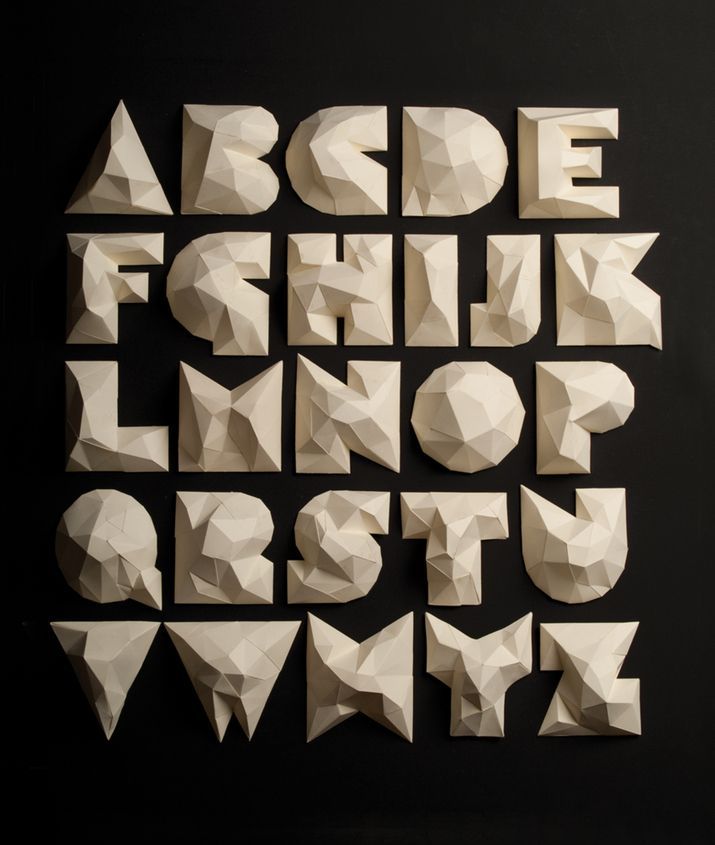
Сила смыслов должна быть подкреплена силой визуализации
Вопросы, которые возникают при работе с шрифтами:
- Как выбрать шрифт?
- Какие параметры необходимо учитывать, чтобы подобрать шрифт для макета?
- Где найти бесплатные шрифты?
Шрифт — инструментом визуальной коммуникации бренда с потребителем. Каждый шрифт имеет свое воздействие на подсознание, задает настроение во время чтения текста.
Прямые вытянутые шрифты отлично подходят для рекламы услуг и продукции, где нужно передать деловое настроение, но не уместны для необычных, уникальных товаров, которым нужно выделиться на фоне конкурентов.
Строгие квадратные шрифты призваны настроить человека на серьезность предоставленной информации.
Где используют:
- реклама промышленных товаров,
- продвижение технологий,
- для социальной рекламы.
Округлые шрифты передают чувство комфорта и уюта. Ассоциируются с добрым отношением бренда к потребителям.
Если у продукта основная аудитория девушки и женщины, то лучше использовать наклонные шрифты, они ассоциируются с легкостью и красотой.
Где используют: салоны красоты, магазины одежды, косметические бренды.